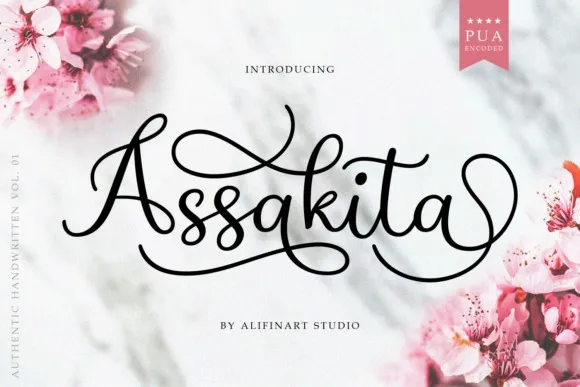
Assakita Calligraphy Font – Download Grátis
Esta é uma fonte de tipo script criada pela Alifinart Studio com um encanto suave e uma forma perfeita, inspirada em belas antigas formas de escrita chinesa. Esta fonte mantém sua influência chamativa na calligrafia clássica ao mesmo tempo que se sente atual e inovadora. Suas múltiplas aplicações atraem uma ampla gama de ideias criativas, desde cartões de visita e títulos até papéis de carta. Esta fonte é perfeita para designers de todos os níveis que buscam um toque sofisticado em seus trabalhos, combinando elegância com uma sensação moderna e vivaz.